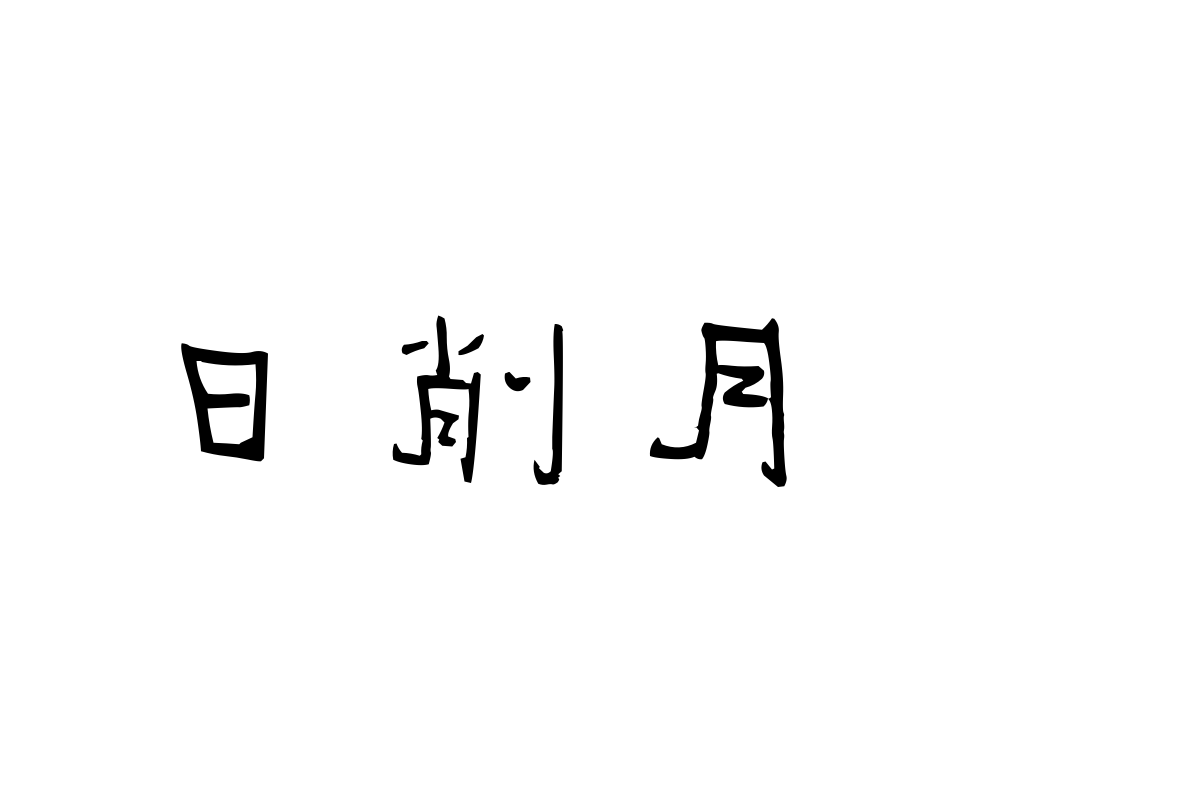
汉仪花农体简是一款具有独特风格的字体,它由汉仪字库出品。这款字体的设计灵感来源于自然,旨在为用户提供一种清新、自然的视觉体验。它的笔画流畅自然,结构简洁明了,给人一种轻松愉悦的感觉。
在这款字体中,每一个笔画都经过精心设计,使得整体看起来既美观又实用。无论是用于标题、正文还是装饰性文字,汉仪花农体简都能展现出其独特的魅力。
此外,汉仪花农体简还具有一定的可读性,适合用于需要强调重点的场合。它的线条粗细适中,既不过于粗犷也不过于纤细,使得阅读起来更加舒适。
总的来说,汉仪花农体简是一款非常适合现代设计需求的字体,无论是用于网站设计、平面设计还是其他任何需要字体的地方,它都能为您的作品增添一份独特的美感。